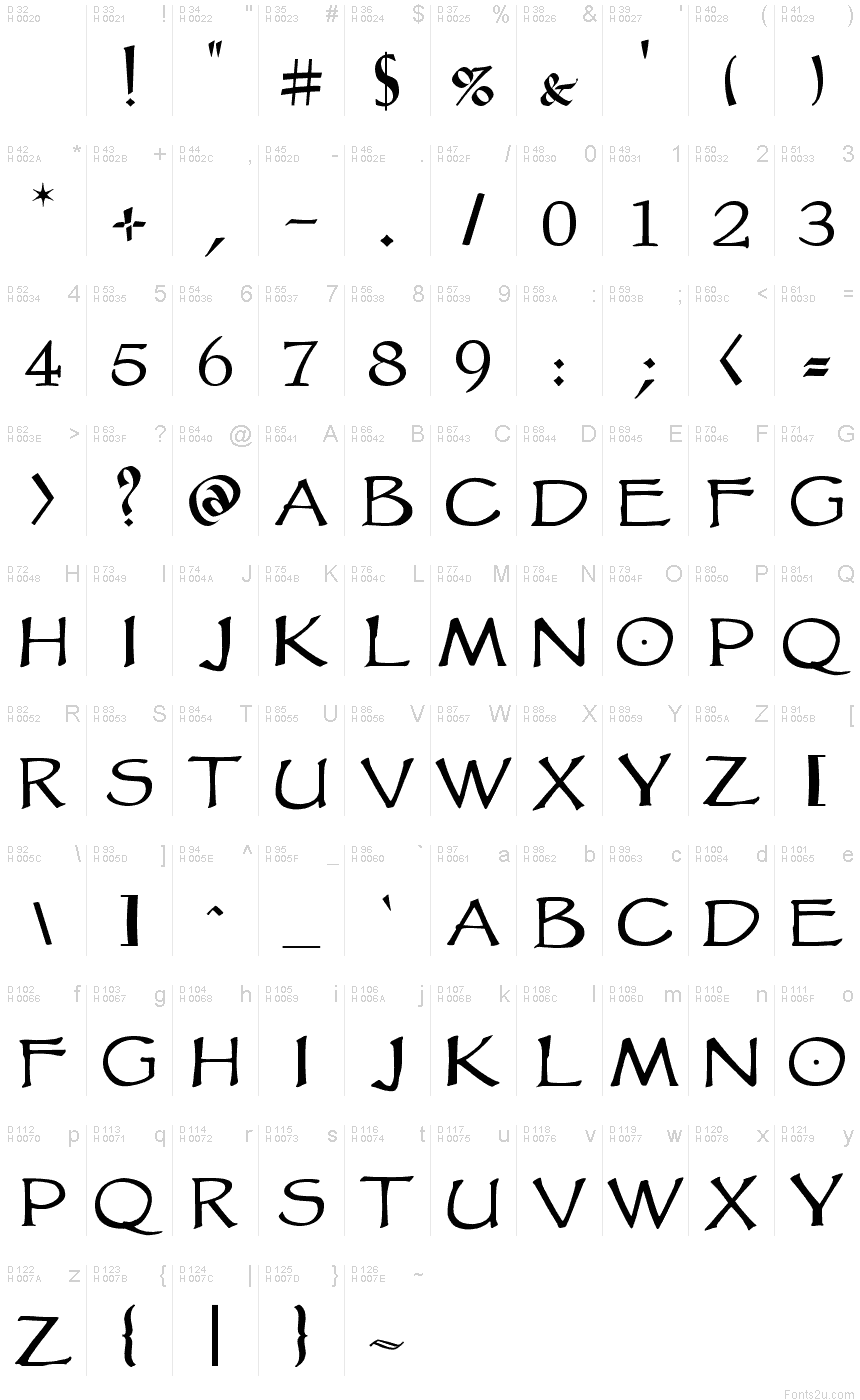
VTC Goblin Hand, prodotta da VTC Vigilante Typeface Corporation, è un font display fantasy in stile rétro con un'aria sorniona, degna di un libro di fiabe. Le maiuscole uniscono curve ampie a tratti affusolati e piccoli uncini, regalando alle lettere un aspetto disegnato a mano e una vivacità «goblin» che evoca vecchi manifesti e un pizzico di malizia.
È la scelta ideale quando vuoi che un titolo appaia teatrale anziché ordinato: copertine di libri, loghi di videogiochi, volantini per Halloween, insegne di pub e testate di fanzine. Essendo un font gratuito, funziona bene anche per titoli brevi, incipit di capitoli e monogrammi, poiché i dettagli arricciati e il ritmo irregolare fanno la loro figura soprattutto in grandi dimensioni.